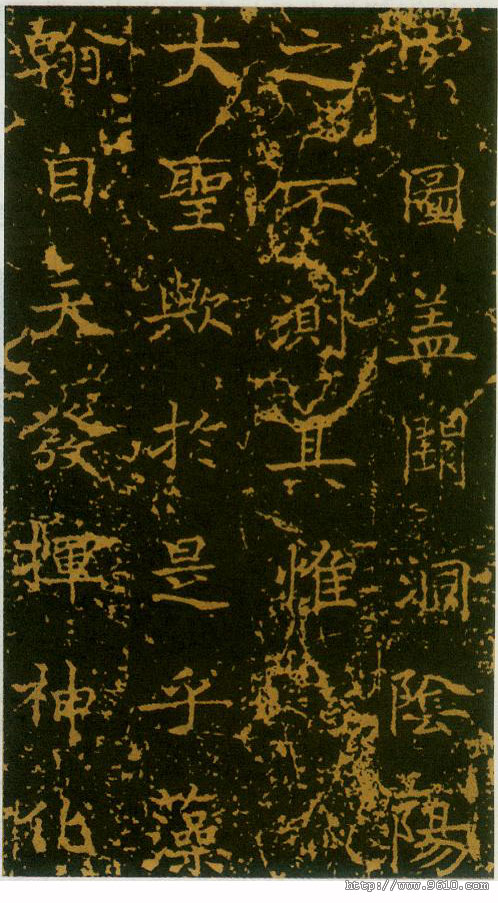
吕向
吕向简介
字子回,泾州(今甘肃泾川)人。开元十年召入翰林,兼集贤院校理(集贤院为唐文学三馆之一,掌秘书图籍等事,设学士、正字等官),侍太子及诸王为文章,官及正议大夫(为文散官名,唐时为二十九阶之第六,正四品上)。吕向曾官迁中书舍人(为中书省署官,掌诏诰、侍从、署敕等,唐时为正五品上),后改工部侍郎。卒,赠华阴太守。
新唐书载:“(吕向)工草隶,能一笔环写百字,若萦发然,世号‘连锦书’。”
吕向《述圣颂碑》(局部) 725年